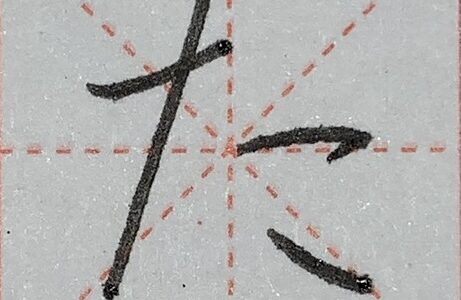
皆さんは、なぜか同じようなミスを繰り返してしまうことはありませんか?
特に、スポーツや技術系のものに関しては、1回の指摘ですぐに修正することが難しい場合があります。
私自身、反復練習がいつの間にか、「これって、反復ミスでは?」となってしまうことがあります。
原因と改善方法が分かっているミスは修正しやすいですが、それらが分からない場合は、そもそも何をどう直したらいいか困ってしまいます。
そこで今回は、そうした盲点に気づく方法を具体例を挙げながらお伝えしていきたいと思います。
①目立つミスそのものに原因があるとは限らない。
例えば、この「皿」という楷書(崩さず、きちっと書く書体のことです。)を見て下さい。
↓手本
↓修正が必要な字
上がお手本で、下が修正が必要な字です。
2つを比較すると、中の2本線が字の違いを生み出していることが分かると思います。
手本と比較した時、一般的には「この2本の縦線がくっつきそうになっているから、間隔を開ければいいんだな。」と考えると思います。
これで、修正できる場合もありますが、いざやってみてもイマイチしっくりこない時があります。
例えば、こちらは中の2本線を直したものですが、何となくお手本とは違う印象を抱くと思います。
「中の2本の縦画は修正したのに、お手本と同じようにならないのはなぜ?」と感じる方もいるでしょう。
このような場合は、中の2本の縦画以外のところに根本原因があると考えた方がいいです。
②1画目はその文字の「前提」を作る
文字は最初が肝心です。
なぜかというと、1画目でその文字の大きさ、その後の点画の流れ、線質の雰囲気などが決まってしまうからです。
1画目があまりうまくいかないと、1画目の欠点をカバーするために2画目がバランスを取ろうとしてしまい、それに続いて3画目、4画目もカバーの為の点画になってしまいます。
例えるなら、人体の骨格の歪みに似ているかもしれませんね。
「骨盤が後ろに倒れているから、それに影響されて猫背になる」みたいな感じです。
1画目は「この字はこの条件のもと書いていってくださいね。」という、2画目以降に向けたメッセージ的な役割を果たします。
なので、お手本を見るときも1画目の位置はしっかり確認しておきましょう。
③ミスと思われる点画の1つ前の画を確認する
先程の「皿」の例で行くと、3,4画目がミスをしているように思われるので、2画目に注目してみます。
今度は、手本と中の2本線を修正した画像を貼ってみますね。
↓手本
↓中の2本線を修正した字
さて、2画目の違いを見抜けるでしょうか。
間違い探しの気分で少し考えてみて下さい。
…(-.-;)ウーン(-。-;)ェー(-.‐)ン?
正解は、「3つの間隔の取り方の違い」です。
これだと、まだざっくりしているので、どうしてここが問題と考えたのか、そうした思考回路に至るかを説明していきますね。
先程、3画目と4画目の間隔が狭くなってしまうということで、その部分だけ直しましたね。
その時、イマイチしっくりこなかった理由は3画目と4画目の間隔が修正された代わりに、1画目と3画目、2画目と4画目の余白が潰されてしまったからです。
3画目と4画目を直す前はそれ以外の部分は特に違和感がありませんでした。
↑よく見ると、1画目と3画目、2画目と4画目はそれぞれ平行になるように書かれています。
↑つまり、3画目と4画目を直したせいで、1画目と3画目、2画目と4画目がそれぞれ平行でなくなってしまった(=余白が潰された)ことが問題なのです。
平行にするためには3画目と4画目に合わせて、1画目と2画目の縦画部分を立てるしかありません。
ということで、今回直すべき個所は1画目と2画目になります。
↓こんな感じです。
どうでしょうか?
字がキュッと、締まりすぎていた感じが緩和されたと思います。
④逆から考えることがポイント
思わしくない結果が出たとき、「なんでこうなってしまったのだろう。」と考える人は多いと思います。
そこから上手く改善できるかどうかは、思考の掘り下げ方にかかっています。
幸い、字に関しては「点画」が証拠として見える形で残ってくれているので、客観的に見やすく、修正しやすいです。
「なぜ?」と繰り返し問いかけ、その都度感覚ではなく、言葉で説明できるくらい字の状態を把握していると、最後は本当に修正すべき点にたどり着きます。
⑤まとめ
以上、同じミスを繰り返している状態から脱出する方法をお伝えさせていただきました。
あまりに上手く書けない状態が続くと、まるで見えない呪いにかけられているようでモヤモヤしてしまうこともあると思います。
そんな時は、やみくもに手を動かすのではなく、いったん立ち止まってお手本と自分の字を分析すると良いと思います。
それでも行き詰った時は、問題を解決するための情報集めとしてインプットに切り替えたり、あるいは一旦その字の練習を保留して他の字にかえたりして、お悩み地獄に陥らないようにしていきましょう。
また、自分1人で解決できない時は、講師の方に頼るのも1つの手です。
試行錯誤しながら、自分のペースで取り組んでいきましょう!